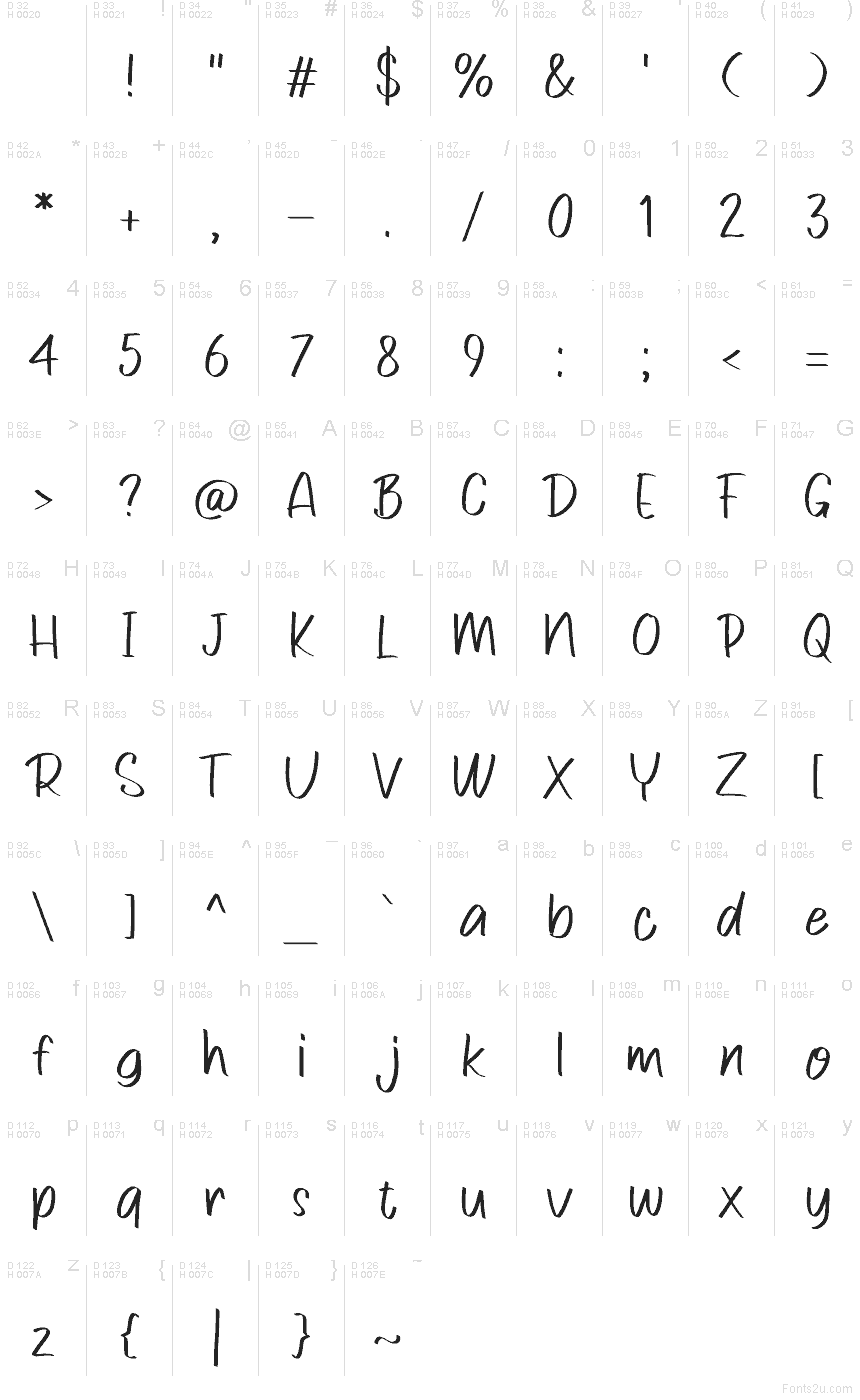
Friday Say
Шрифт Friday Say від Hello Good Studio — це безкоштовний рукописний шрифт із розслабленим, нерівномірним ритмом і високими, стрункими знаками. Його форми виглядають так, ніби їх намалювали від руки одним плавним рухом: з легким тремтінням, м'якими кривими та невимушеним нахилом, що позбавляє його зайвої суворості.
Friday Say чудово підійде для запрошень, графіки з цитатами, логотипів, постів у соцмережах, пакування та персональної канцелярії, оскільки він додає відчуття рукописного підпису, зберігаючи при цьому просту структуру. Цей безкоштовний шрифт також хороший для коротких заголовків, де важливіше створити теплий, неформальний настрій, ніж досягти вивіреного чи строгого корпоративного вигляду.